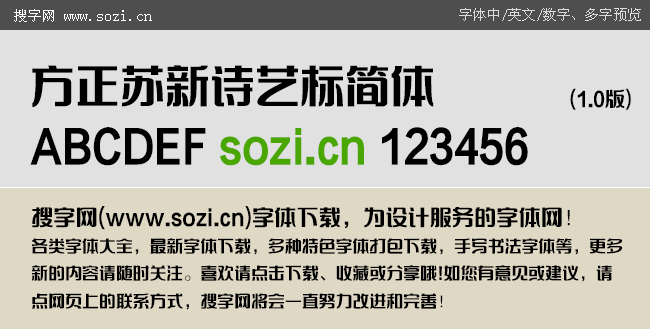
方正蘇新詩藝標(biāo)簡體
搜字網(wǎng)提供一款非常藝術(shù)的方正蘇新詩藝標(biāo)簡體下載,方正蘇新詩藝標(biāo)簡體是一款以綜藝體為原形進(jìn)行藝術(shù)設(shè)計(jì)的字體,該字體極具藝術(shù)感,簡潔大方,適用于包裝印刷、廣告設(shè)計(jì)、平面設(shè)計(jì)、書籍報(bào)紙等領(lǐng)域。